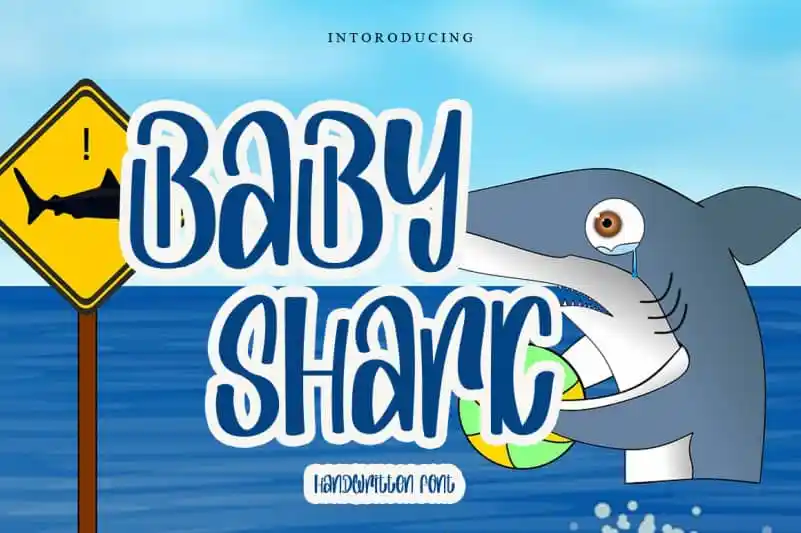
Baby Shark Display Font – Download Grátis
A fonte ‘Baby Shark Display Font’ é uma escolha perfeita para aqueles que querem adicionar um toque animado à suas criações digitais, seja para design infantil, nomes de marca, capas de livros ou cartazes. Ideal tanto para elementos divertidos e quirkiness quanto para estilos mais formais, essa fonte é uma opção ótima para quem busca beleza em qualquer projeto. Seja para desenhos animados, jogos infantis ou até mesmo frases motivacionais, a ‘Baby Shark Display Font’ traz alegria e originalidade ao design de texto. Essa fonte é perfeita para aqueles que buscam uma maneira criativa de adicionar um toque especial aos seus trabalhos digitais, especialmente em categorias como design infantojuvenil, marketing, literatura ou arte gráfica. Aproveite a diversão da ‘Baby Shark Display Font’ para deixar sua marca mais divertida e impactante.